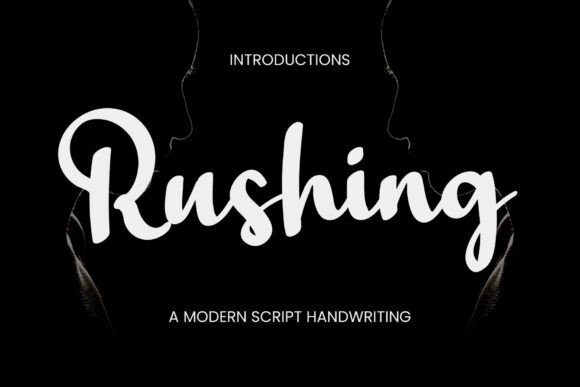
Rushing
Se stai cercando risorse di alta qualità come Rushing, questo pacchetto premium è una scelta fantastica per i tuoi progetti creativi.
Realizzato con precisione, Rushing fornisce vettori puliti, tipografia fluida e una licenza commerciale per la massima tranquillità.